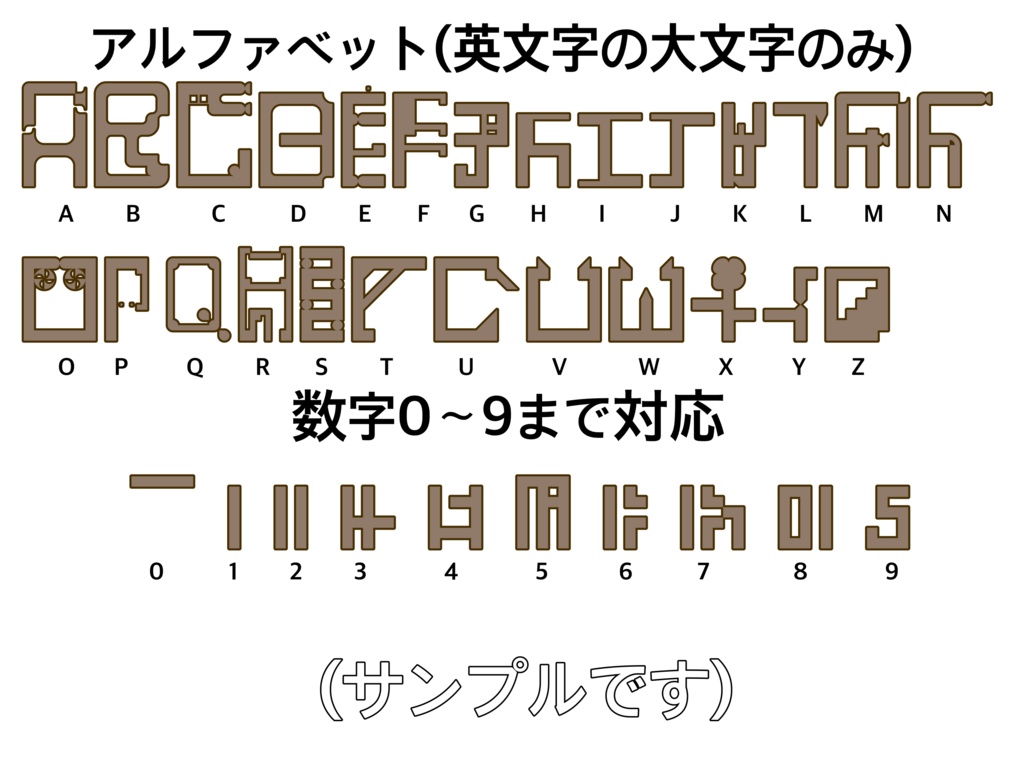
〈フォント〉What is this? 【ナゾフォント】
閲覧ありがとうございます! “あのゲーム内の文字を作りたい…!”という思いで制作されました 【ナゾフォント】であります! 頑張れば解読できそうな文字やどう頑張っても解読できない(?)文字を描いてみました。 ぜひ使ってみて下さい! ※段落がございます。スマートフォン端末では表示されない場合がございますので、PCサイト版で確認してください。
考えられる用途 ・古代遺跡の文字 ・パラレルワールドの言語 ect…